Efectos y Distorsiones Tipográficas
Me gustaría saber como se pueden realizar este tipo de distorsiones, perspectivas y efectos jugando con las tipos.
Estoy diseñando una marca y me gustaría aplicarlo, por lo que lo interesante sería realizarlo en Illustrator para que fuera un archivo vectorial...
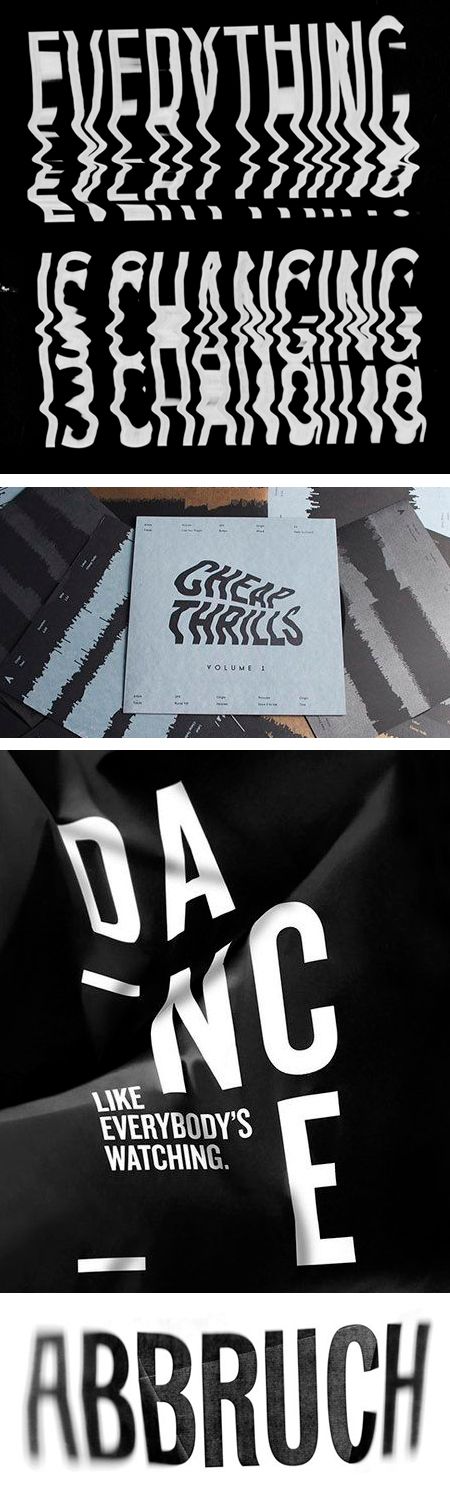
Las dos primeras es jugando con el escáner. Mientras estás escaneando una hoja la vas moviendo hacia abajo o dónde quieras que distorsione, tendrás que hacer varias pruebas hasta que te guste alguna.
La última es una foto directa y editada un poco para dar el contraste y desenfoque.
La de 'Dance' parece un mapa de desplazamiento en Photoshop y/o en algún software 3D.
A parte de estas aplicaciones, puedes probar de imprimir la composición sobre un plástico y calentarlo con un secador para estirarlo/deformarlo, lo hice con unas pegatas que tenía en el skate https://instagram.com/p/vQyKfKPDlS
Al final lo mejor para ello es experimentar, be curious ;)